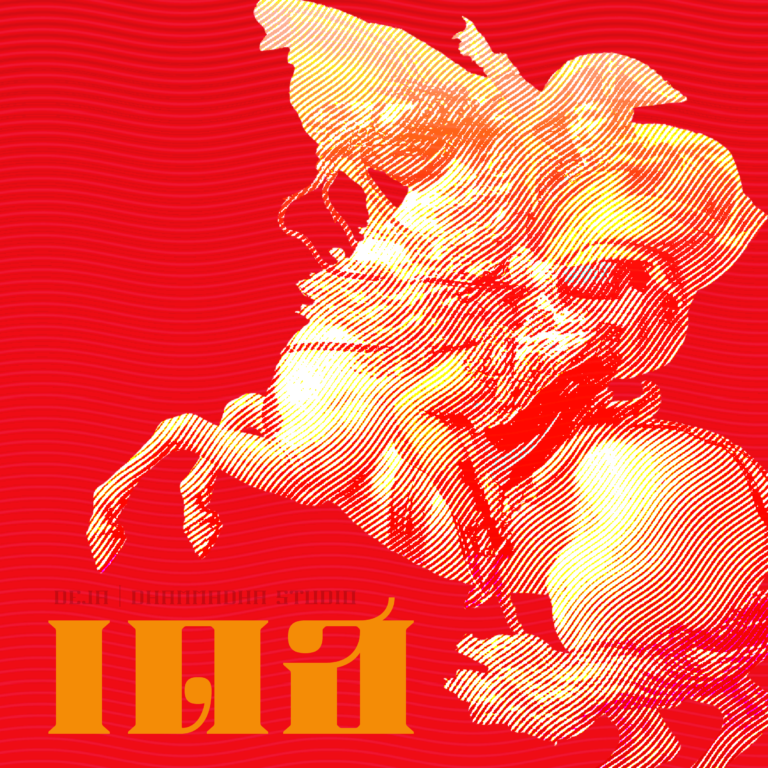
ถั่ว | TOURR
“ถั่ว | TOURR” คือ ฟอนต์ดิสเพลย์สไตล์ลายมือที่พกพาความสนุกสนานและเป็นกันเองมาแบบเต็มพิกัด ฟอนต์นี้เริ่มต้นจากการสเก็ตช์อย่างอิสระบนหน้ากระดาษ ก่อนจะนำมาวาดเส้นสายใหม่บนคอมพิวเตอร์อย่างพิถีพิถัน ทำให้ได้ตัวอักษรที่มีกลิ่นอายความสนุกแบบงานคราฟต์ แต่ยังคงความเนี้ยบและจัดวางได้สวยงามลงตัว
เนิร์ดเนิร์ด | NerdNerd
เบื่อไหม? จดสรุปทีไรลายมือไม่เคยรักดี… มาเปลี่ยนโน้ตให้น่าอ่านระดับ 10/10 ด้วยฟอนต์ “เนิร์ดเนิร์ด | NerdNerd” ฟอนต์สุดเนิร์ดสำหรับเนิร์ดสายจด !
ดูลิง | DOOLYNX
เปลี่ยนงานให้ดูมีชีวิตชีวาขึ้นอีกขั้น!! ด้วย “ดูลิง | DOOLYNX” ฟอนต์ดิสเพลย์วาดมือสุดคิวท์ ที่จะนำความคิดสร้างสรรค์อันไร้ขีดจำกัดมาสู่โปรเจกต์ของคุณ กับรูปทรงที่โค้งมน อวบอ้วน ให้ความรู้สึกสนุกสนานโดดเด่นไม่เหมือนใคร
สุขสราญ | SUKSARANN
ชุดฟอนต์พาดหัว ที่จะนำความสุขในอดีตข้ามเวลากลับมาเติมเต็มคอนเทนท์ของคุณด้วยความทรงจำที่ดี
กร่อน | KRONN
ส่วนผสมที่ลงตัวระหว่างความนุ่มนวลและความบึกบึน ฟอนต์พาดหัวตัวหนา ที่ร่างแบบด้วยการเขียนมือ บุคลิกเรียบง่าย แต่แสดงตัวตนได้อย่างชัดเจน
แฮนดี้ริทเทิ่น | HANDYWRITTEN
REMAKE PROJECT II จากฟอนต์สุดฮิต ฟอนต์ “แฮนดี้ไรท์“พัฒนาขึ้นใหม่ อัปเดต และอัปเกรดความสามารถแบบก้าวกระโดดยังคงความน่ารัก ใช้งานง่าย เป็นกันเอง เหมือนเดิม
มณี นิว | MANI NEUE
REMAKE PROJECT จากฟอนต์สุดฮิต ฟอนต์ “มณี-เมขลา”พัฒนาขึ้นใหม่ อัปเดต และอัปเกรดความสามารถแบบก้าวกระโดดยังคงความน่ารัก ใช้งานง่าย เป็นกันเอง เหมือนเดิม
เดช | DEJA
ชุดอักษรที่มีต้นแบบจากใบปิดหนังยุคก่อนถอดจุดเด่นสะดุดตาจากต้นฉบับ แล้วดีไซน์เพิ่มเติมประกอบกลับเข้าไปเพื่อให้เป็นชุดอักษรที่ทรงพลัง มีอำนาจ น่าเกรงขามทั้งยังมีความหรูหรา สวยงาม เป็นสำคัญ
ขมิ้น | KAMINN
ชุดฟอนต์พาดหัว เก่า และเก๋าโดดเด้งแรงบันดาลสุดหัวใจ จาก ปก LP แม่นางนกขมิ้นของ คุณสมยศ ทัศนพันธ์ ศิลปินเพลงไทยลูกทุ่งรางวัลแผ่นเสียงทองคำพระราชทาน จากบทเพลง “ช่อทิพย์รวงทอง”
บ้อง | BONGG
ชุดฟอนต์พาดหัว เป็น Display Font  ทรงสูงประหยัดพื้นที่ มีส่วนเว้าโค้งแบบกระบอกข้าวหลามเพิ่มความเคลื่อนไหวในเนื้อความ
ป๋วย | PUAI
ฟอนต์ลายมือ จากแอดมินอ้วน เพจ RUNNING TORTOISEเพจวิ่งที่ไม่ค่อยอัพเดตอะไรเท่าไร เจ้าของไอเดียฟอนต์สุดจ๊าบ ดองเต่า | DONGTAO
ถัง | TANKK
ชุดฟอนต์ย้อนวัย เข้มแข็ง บึกบึนใช้พาดหัว เป็น Display Font ได้กระแทกสายตาอย่าใช้เป็นเนื้อความ Text Font ..อันนี้ไม่เหมาะ
สุรัตนา | SURATANA
เปิดตัวมาพร้อมกับพี่น้องฝาแฝดในตระกูลแต่บุคลิกแตกต่างเพื่อการใช้งานที่หลากหลายมากขึ้นไม่ว่าจะเหนือระดับอย่าง Serif (ในชื่อ SURATANA)หรือเรียบหรูแบบ High Contrast Sans (ในชื่อ SURATANA SANS)
ศึกษา | SUKSA
ใช้พาดหัว เป็น Display Font ก็สุดเท่ใช้เป็นเนื้อความ Text Font ก็สุดเก๋